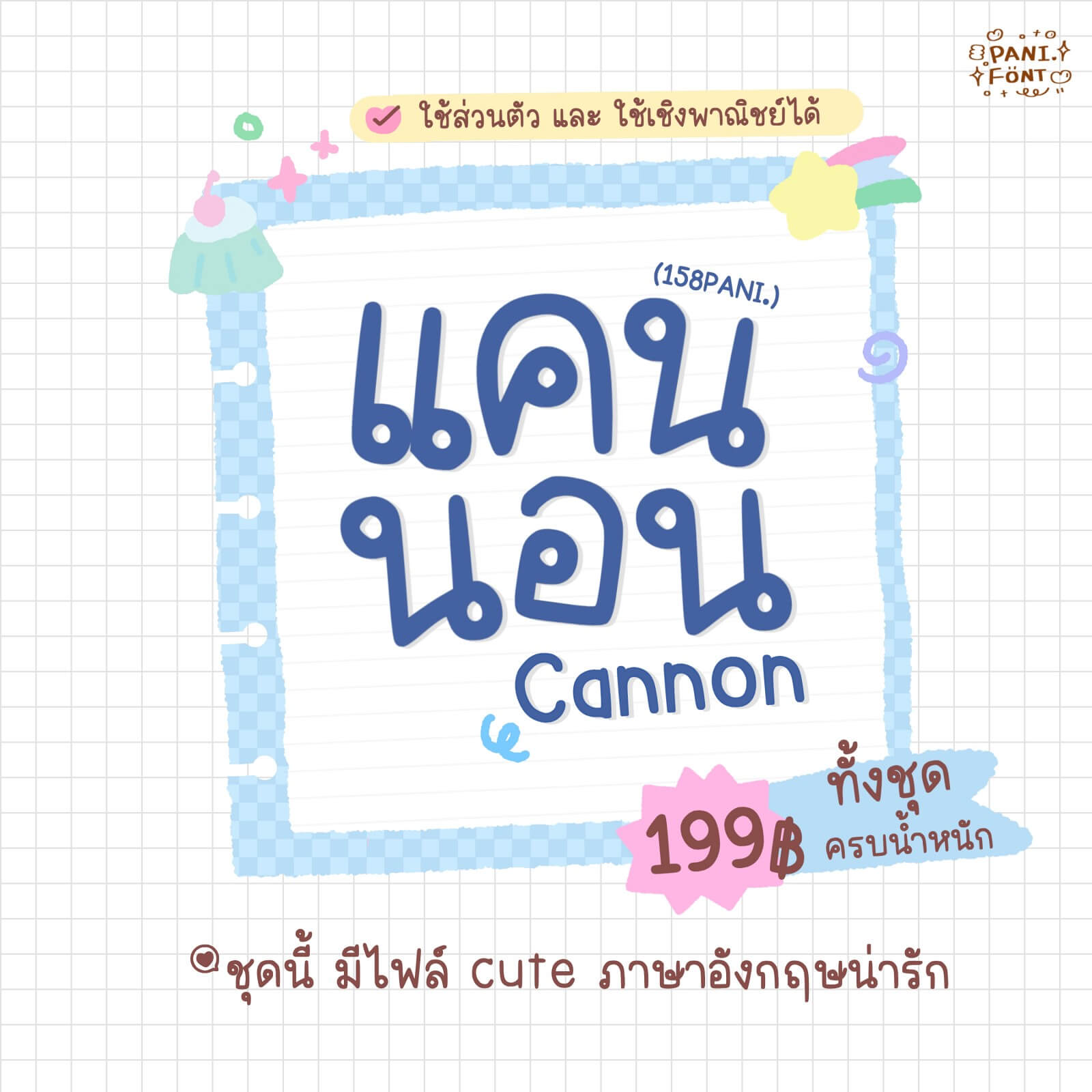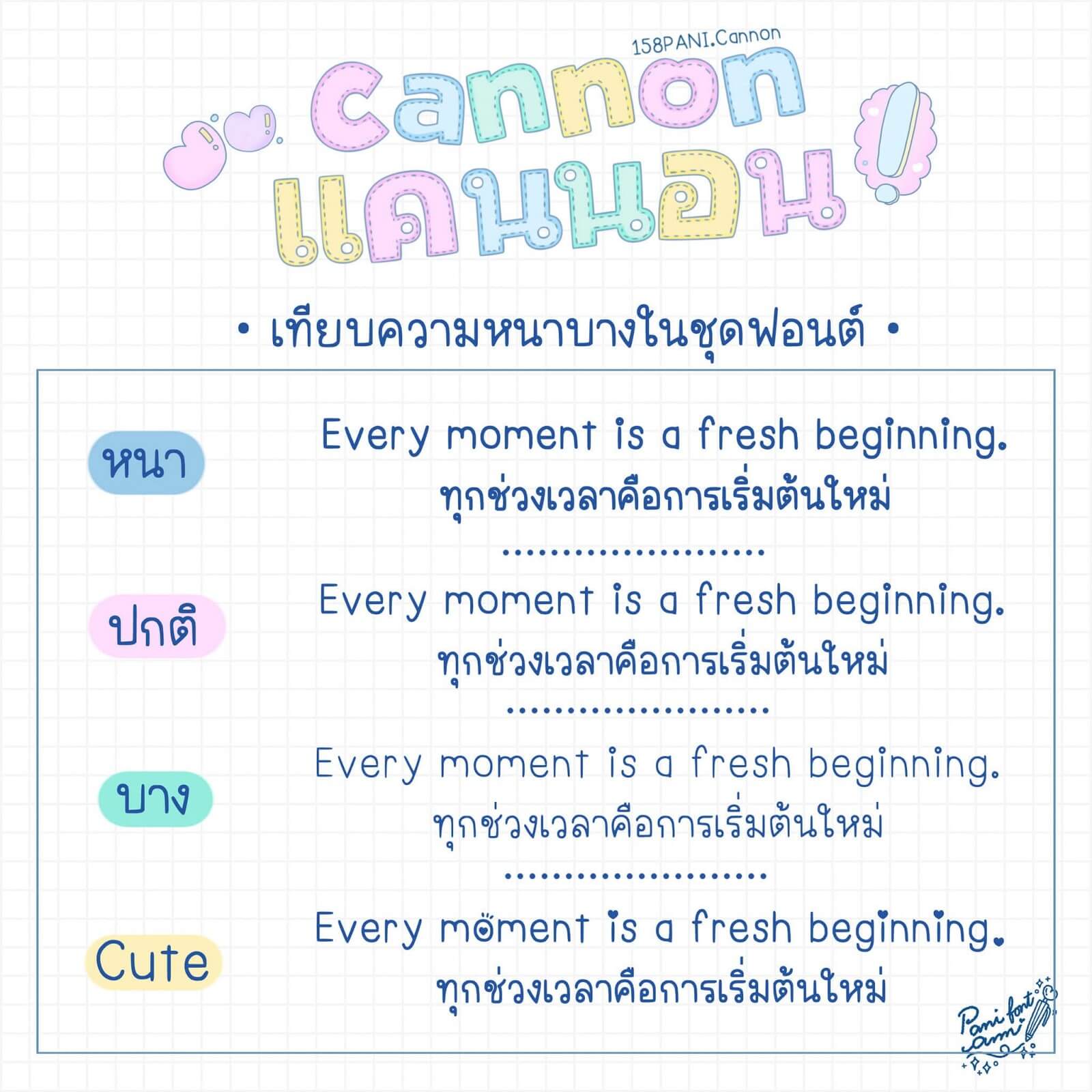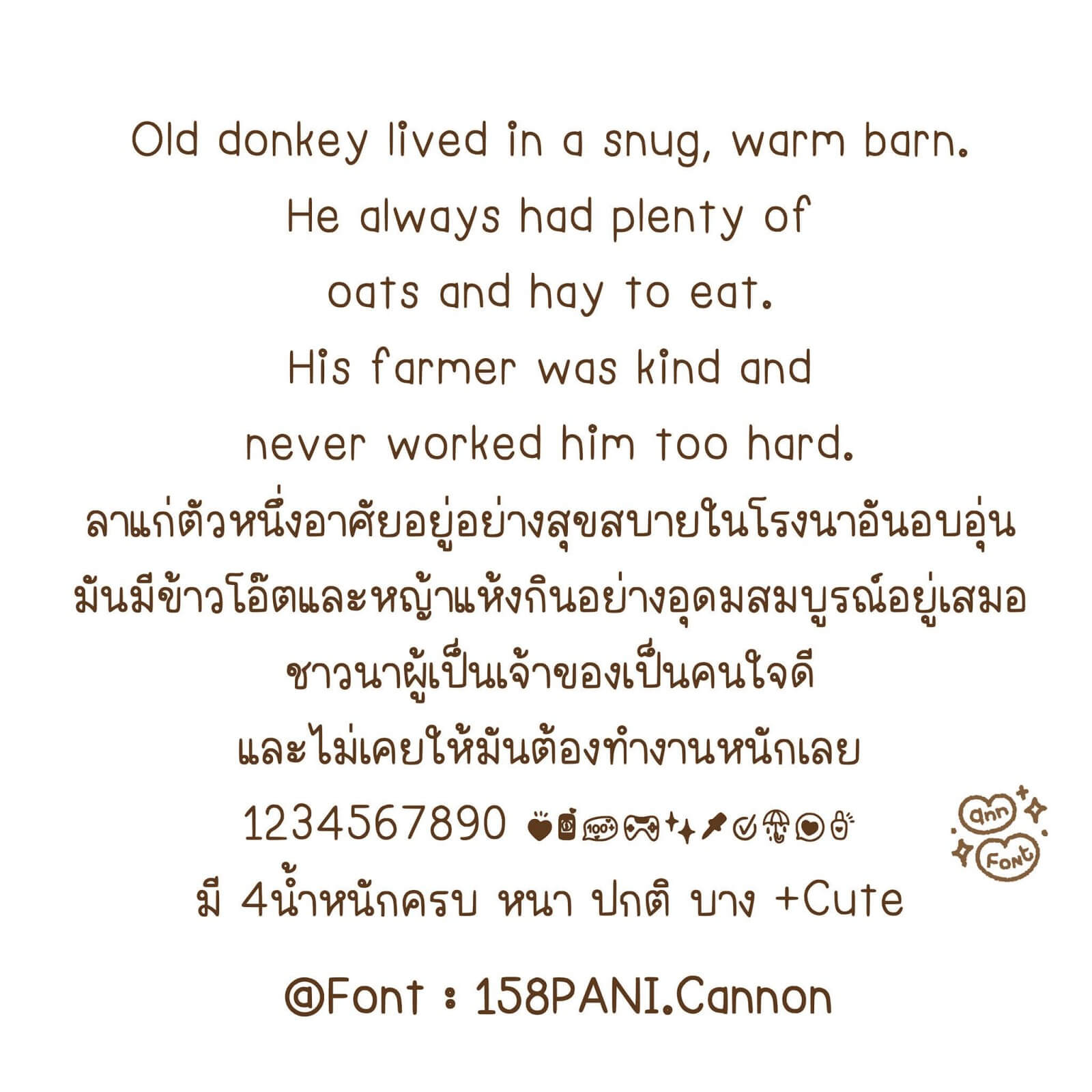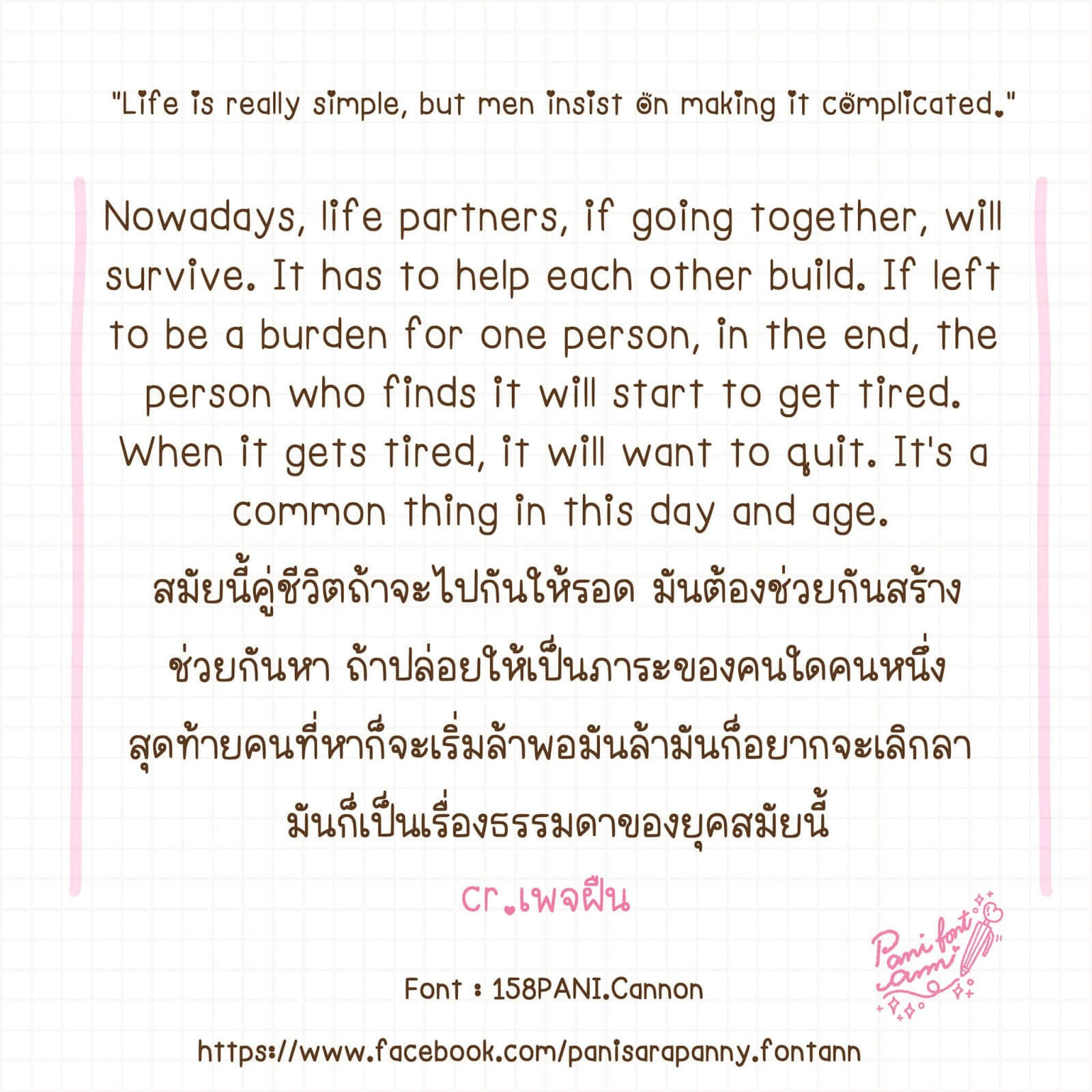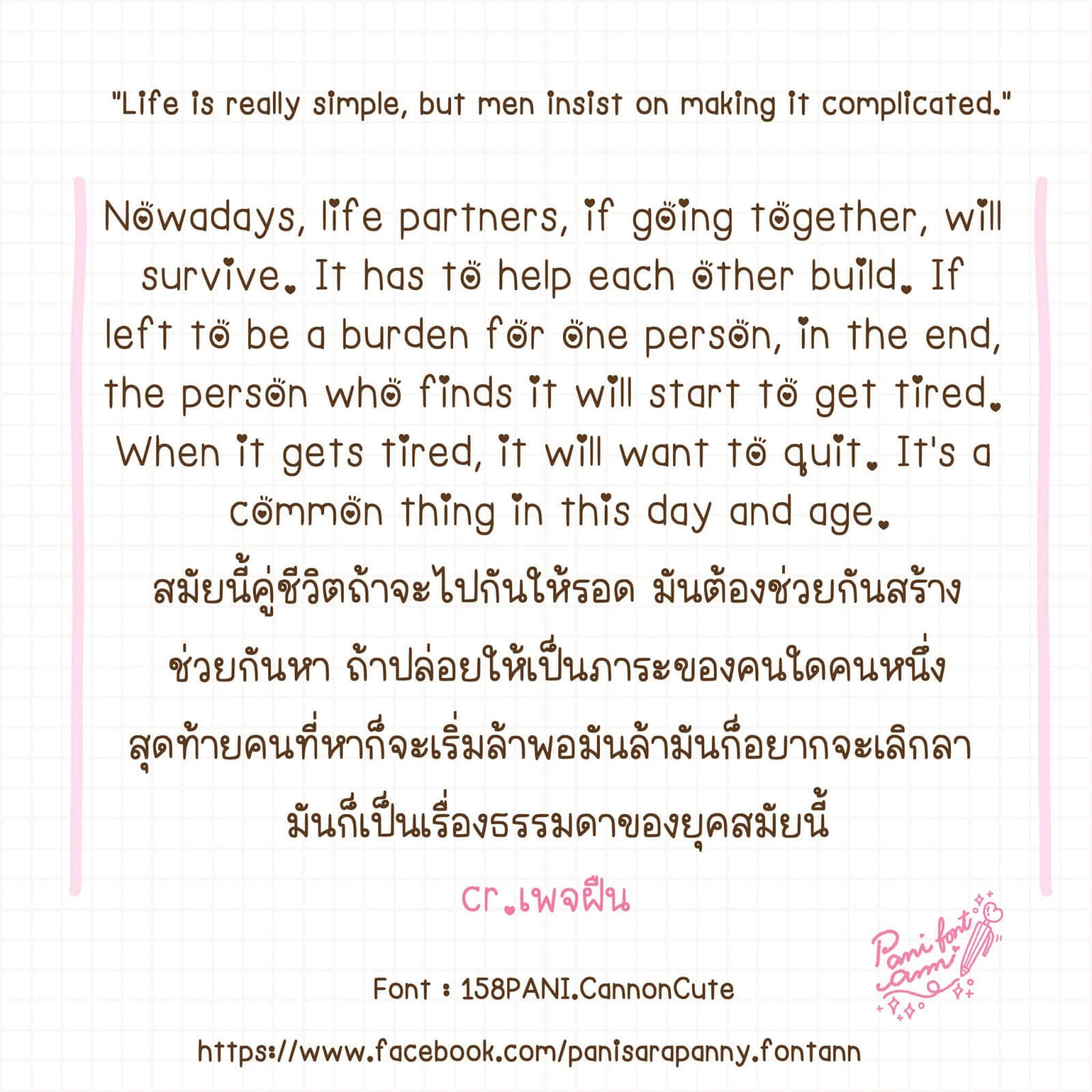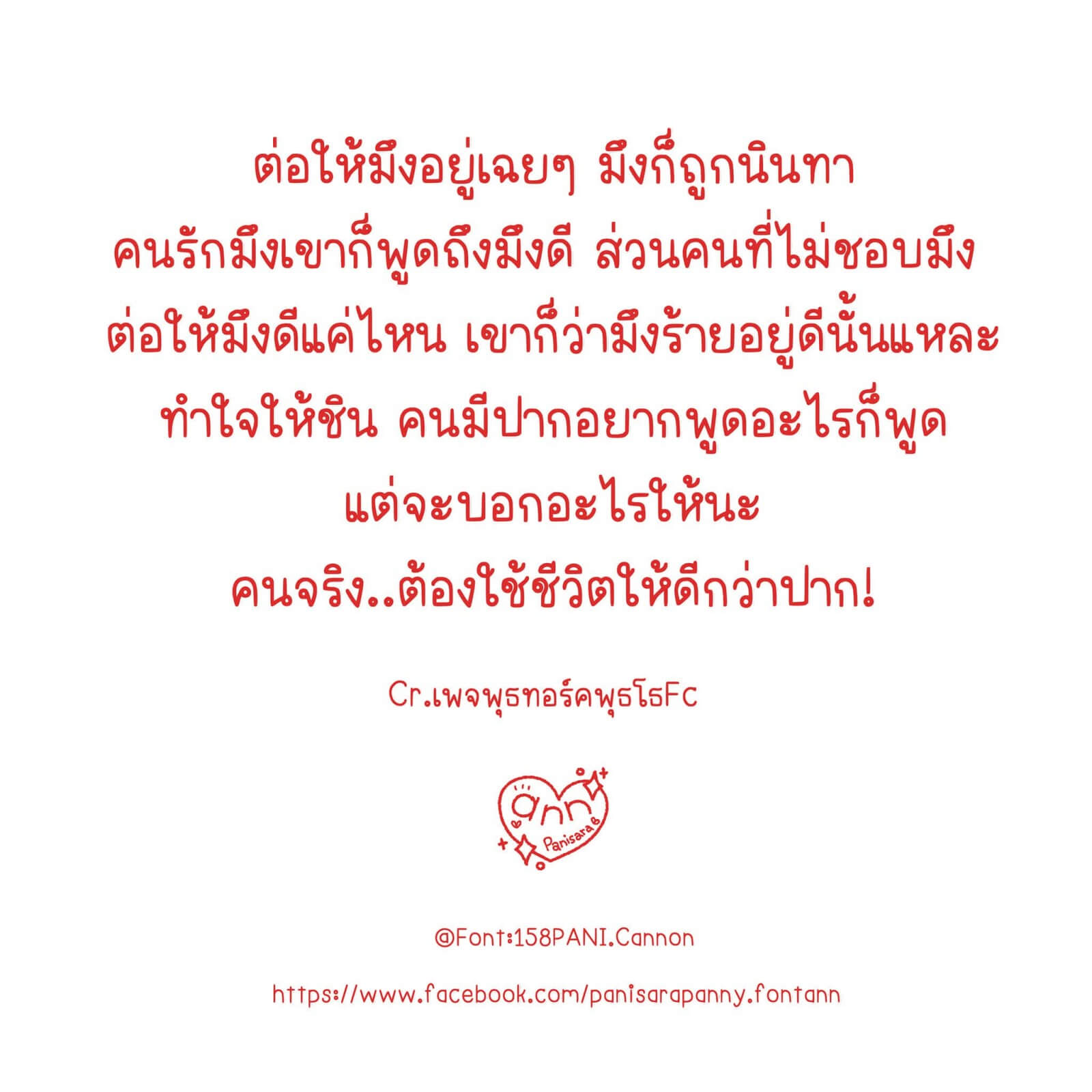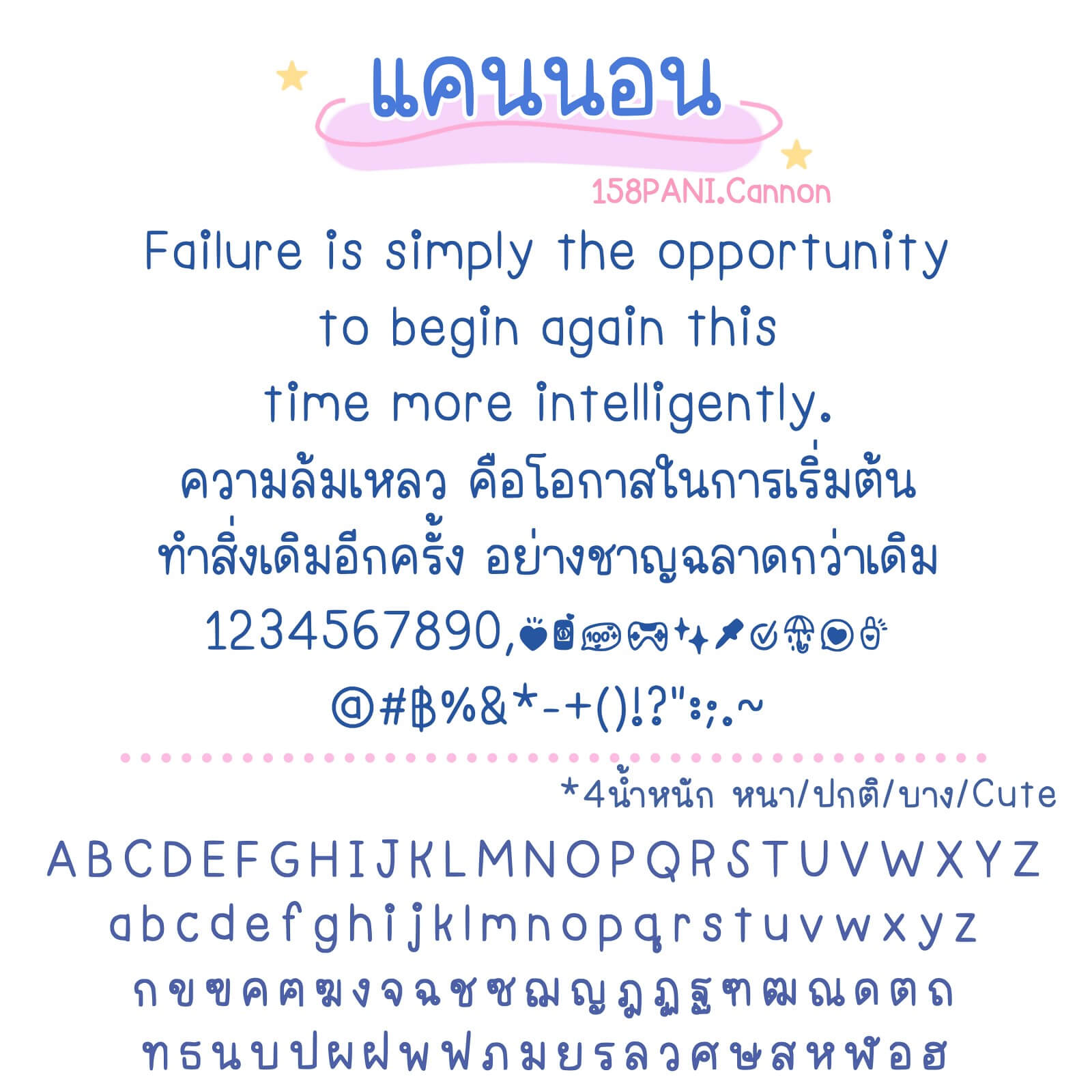
ฟอนต์ PANI.แคนนอน – ฟอนต์แนวเรียบร้อย แต่ยังคงน่ารัก ใช้งานรายละเอียด จดโน้ต ตั้งเป็นฟอนต์เครื่อง
Ebook อ่านง่าย และเลขไทยยังเป็นอีโมจิ ไว้ตกแต่ง เพิ่มความน่ารักให้การใช้งาน
ฟอนต์มี 4 ไฟล์ – น้ำหนัก บาง ปกติ หนา Cute
PANI.แคนนอน